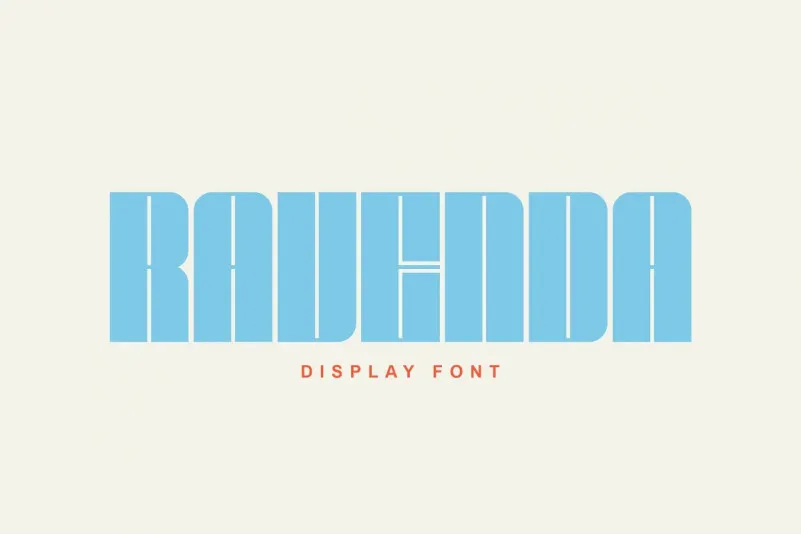
Ravenda Font – Download Grátis
A Ravenda é uma fonte Display desenvolvida com cuidado para capturar a beleza harmônica dos caracteres e destacar suas linhas altas elevadas, criando um design compacto que transmite autenticidade e profundidade. Ideal para dar ênfase a títulos, esta fonte vem em uma variedade completa de letras maiúsculas, números e pontuação, tornando-a versátil para uso em diversos ambientes, desde shows e eventos esportivos até criação de logotipos. A Ravenda foi criada com o objetivo de destacar e impactar visualmente qualquer texto à qual é aplicado, garantindo um design imponente e sofisticado.